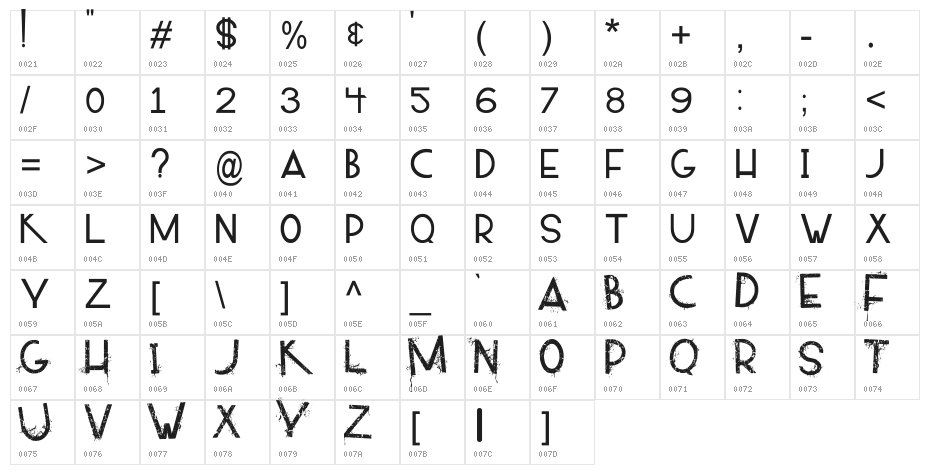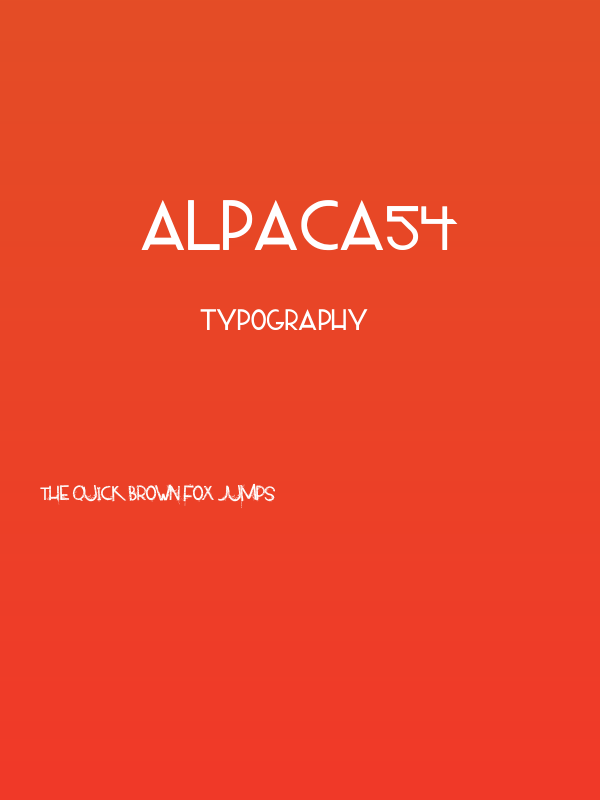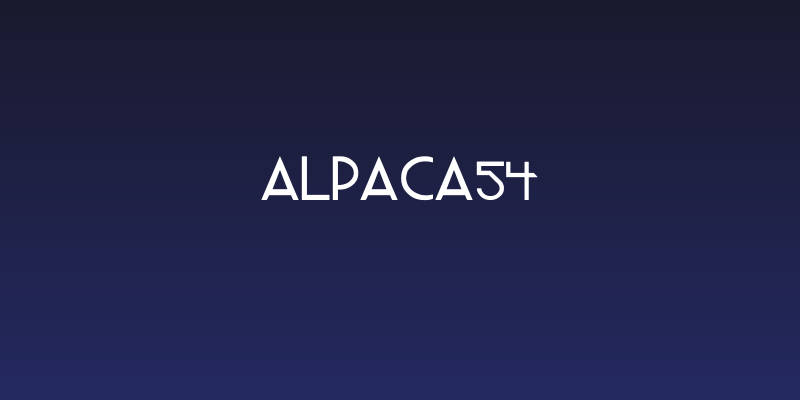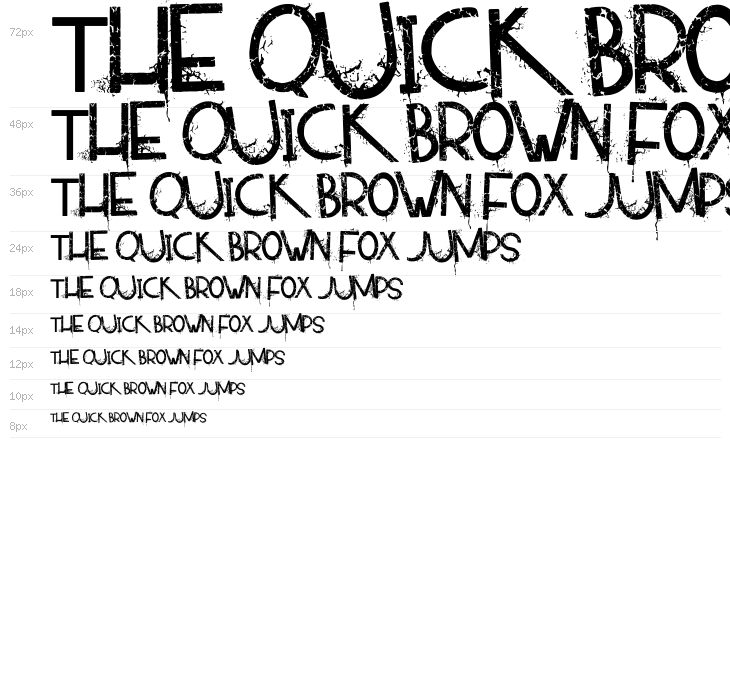
ALPACA54 Font
✎ Distorted Eroded
| النمط العام | Modern, Edgy, Grunge |
| مشاريع مقترحة | Ideal for posters, album covers, branding for edgy products, and any project needing a strong visual impact. |